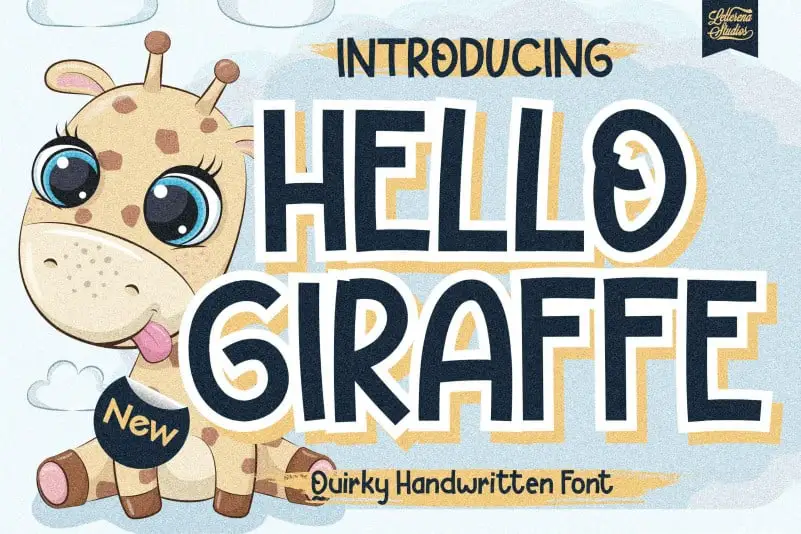
Hello Giraffe Display Font – Download Grátis
A fonte “Hello Giraffe Display Font” é uma escolha perfeita para quem busca uma mistura criativa e forte no seu projeto visual. Sua tipografia peculiar oferece um toque divertido e moderno que será capaz de destacar qualquer design. Através deste elegante estilo de texto, você poderá trazer vida à sua página ou logotipo, garantindo que ele seja notado e agradado ao público. Seja para adesivos, publicidade online ou até mesmo para criações digitais, essa fonte irá reforçar o seu design. O designer letterenastudios criou algo único e envolvente com “Hello Giraffe Display Font”, um verdadeiro atalho para qualquer projeto que esteja em busca de personalidade e estilo. Não hesite em experimentar esta fonte, você não ficará desapontado.